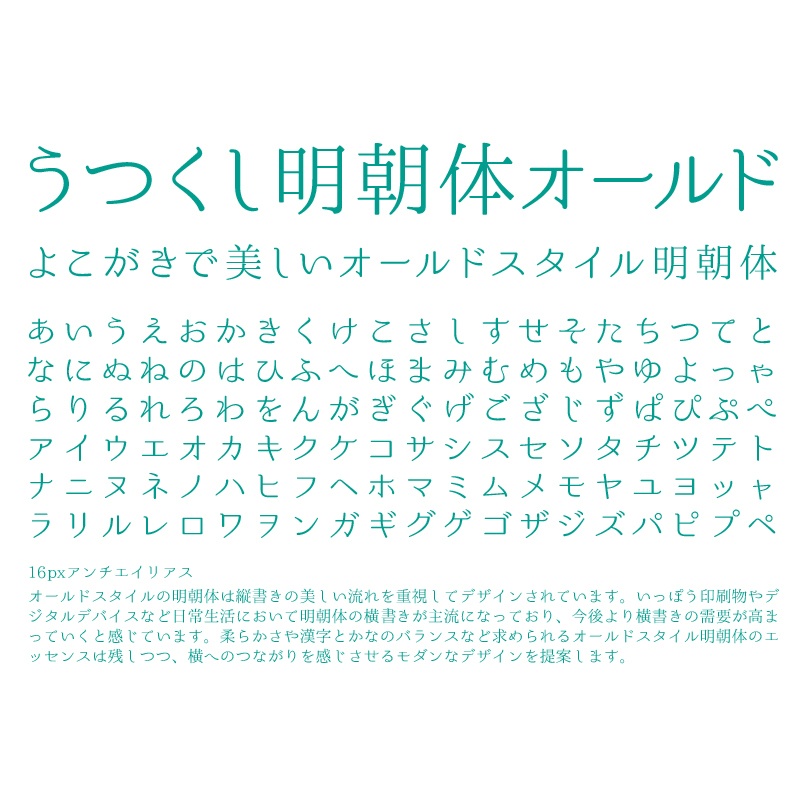
美丽明朝体
字体风格: 明朝体
古典明朝体基本上是以竖排的美丽流畅为重点设计的。
在日常生活中,无论是印刷品还是数字设备,横排的明朝体已经成为主流,我感觉未来横排的需求会进一步增加。
“うつくし明朝体+” 在保留古典明朝体的要素,如柔和、复古的风味以及汉字和假名的平衡等的基础上,采用了更现代的设计,强调与横排的连接感。垂直和水平的线条都是笔直的,同时也广泛使用了斜线的直线设计。这是对新概念的古典系列明朝体的设计提案。平假名和片假名赢得了2014年日本印刷年鉴最佳作品奖。